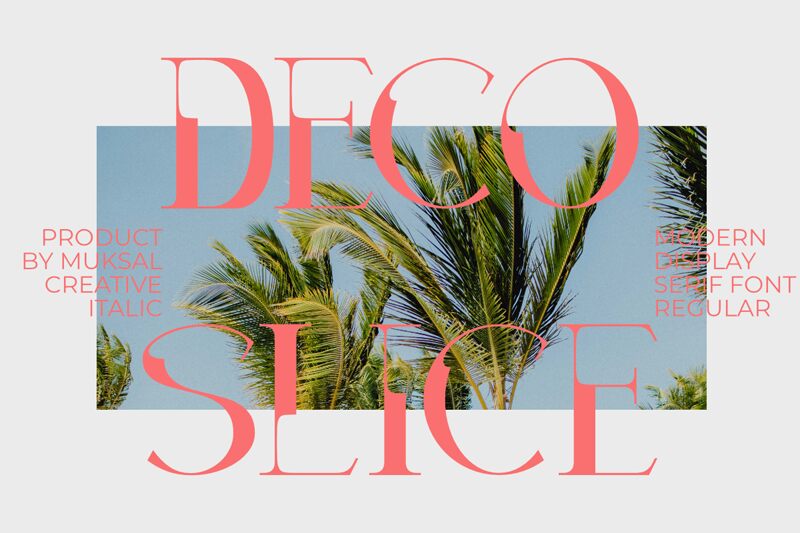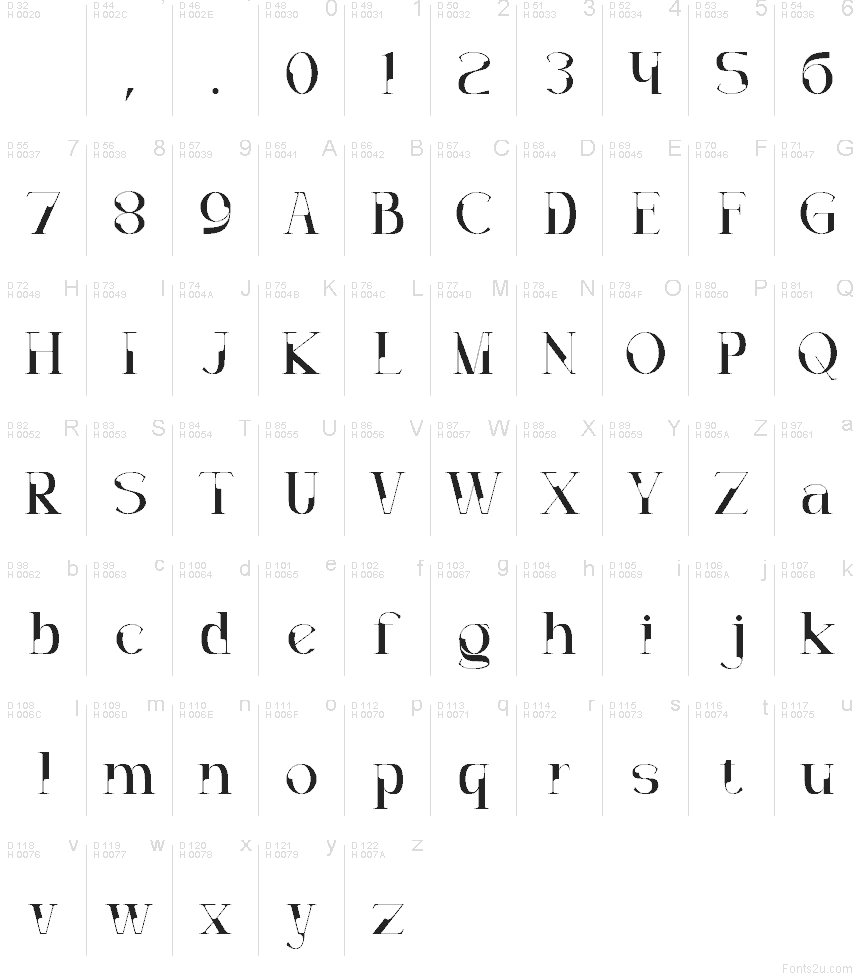
تعد Decoslice من تصميم Decolice (Muksal Creative) خط عرض مجاني مستوحى من طراز Art Deco، يتميز بمنحنيات سوداء انسيابية وشرائح بيضاء حادة تخترق الحروف كأنها ألواح مطعمة. يمنح هذا التباين المتكرر الحروف إيقاعاً أنيقاً يشبه تصاميم الملصقات، حيث تحافظ الصور الظلية المستديرة على رشاقتها بينما تخلق الفراغات المحفورة لمسة غرافيكية حادة وواضحة.
يعد هذا الخط خياراً مثالياً لقوائم الكوكتيل، وتغليف العلامات التجارية الفاخرة، ودعوات الفعاليات، وملصقات الأفلام، وهويات العلامات التجارية في مجال التجميل، حيث تكون الرزانة الزخرفية أكثر أهمية من مجرد الاستخدام الوظيفي. تضفي التفاصيل الداخلية المقطوعة على الكلمات القصيرة حضوراً راقياً يفوح بعبق الماضي، مما يجعل العناوين والشعارات تبدو كقطع فنية متقنة بدلاً من كونها مجرد زخارف.